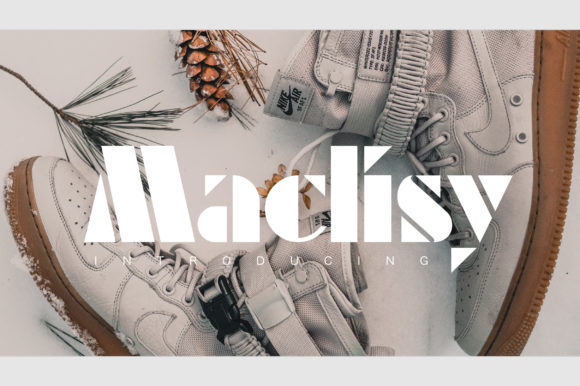
Creativefabrica Maclisy Font
[Creativefabrica] Maclisy Font
Maclisy - это уникальный и интересный шрифт.
Немного причудливый, этот шрифт отлично подходит для самых разных контекстов!